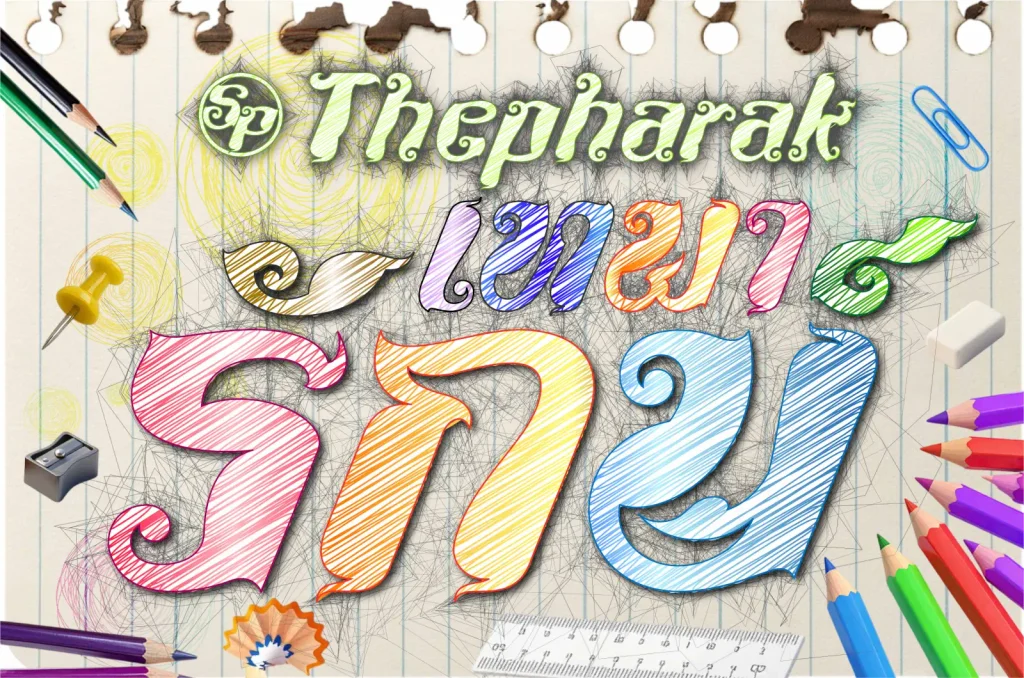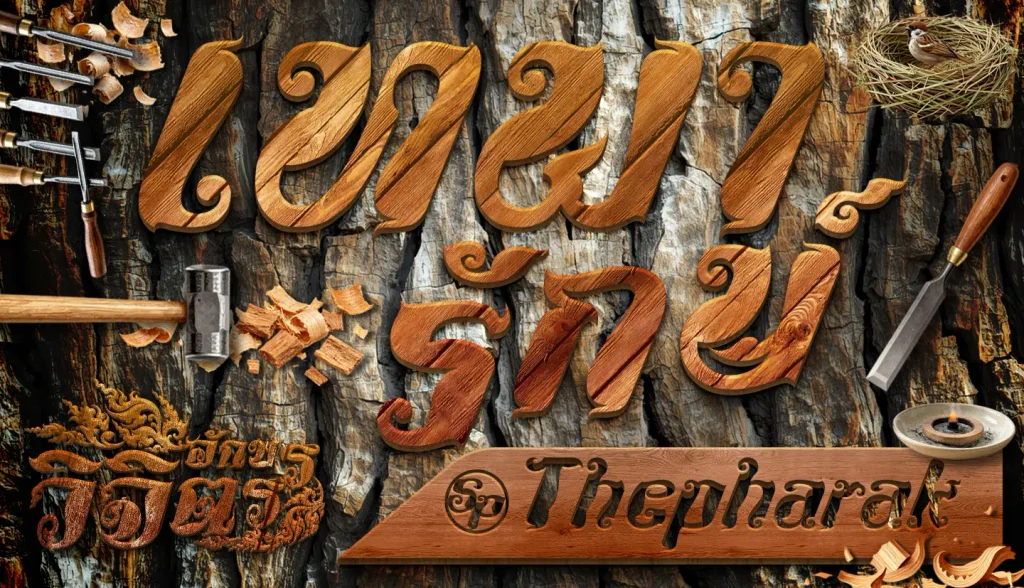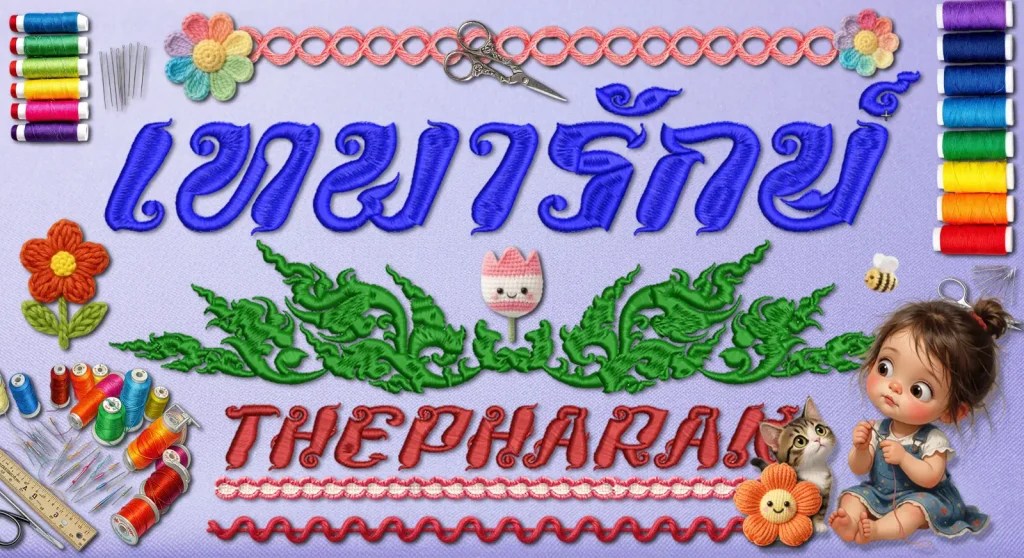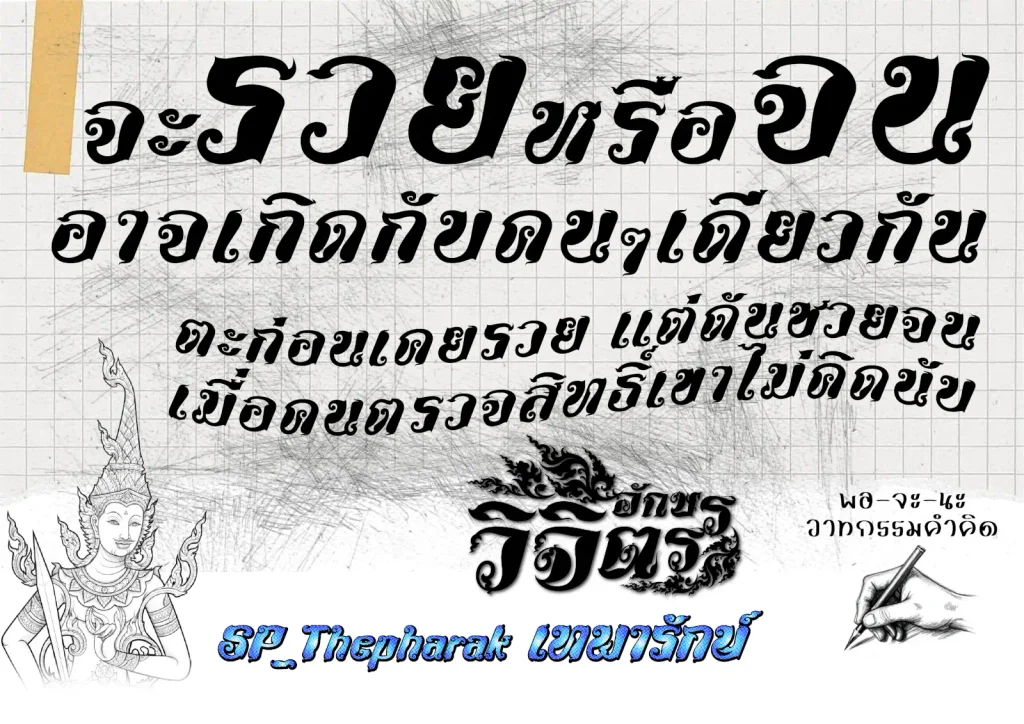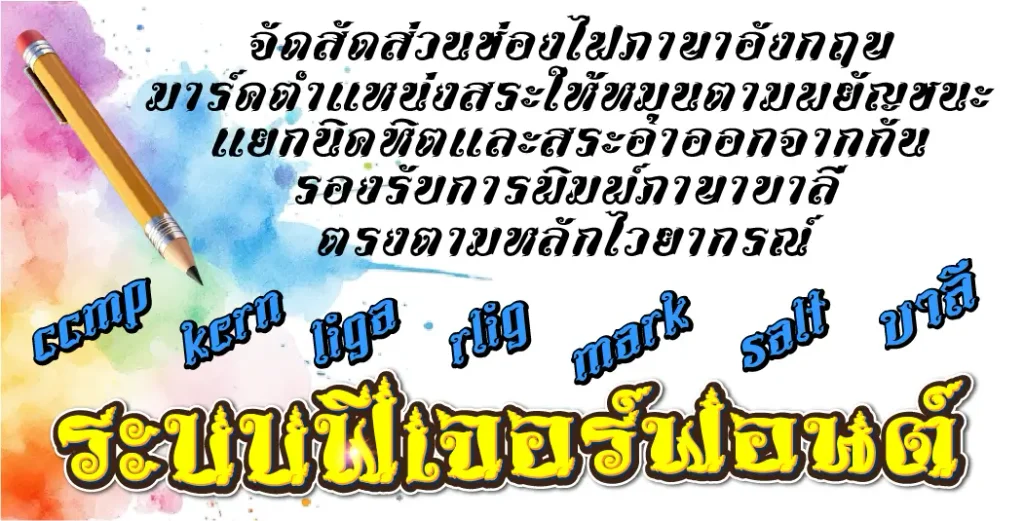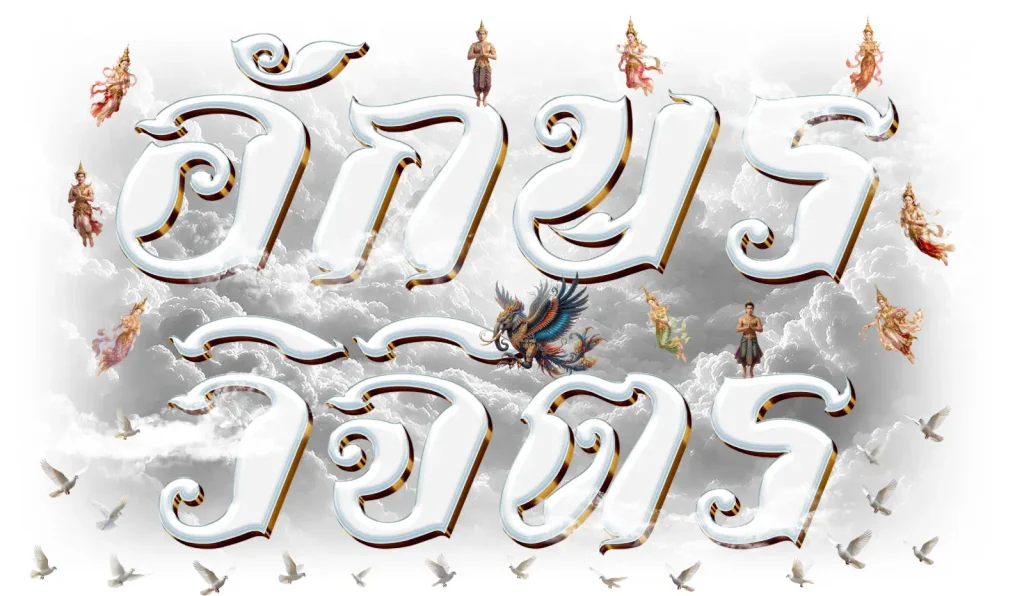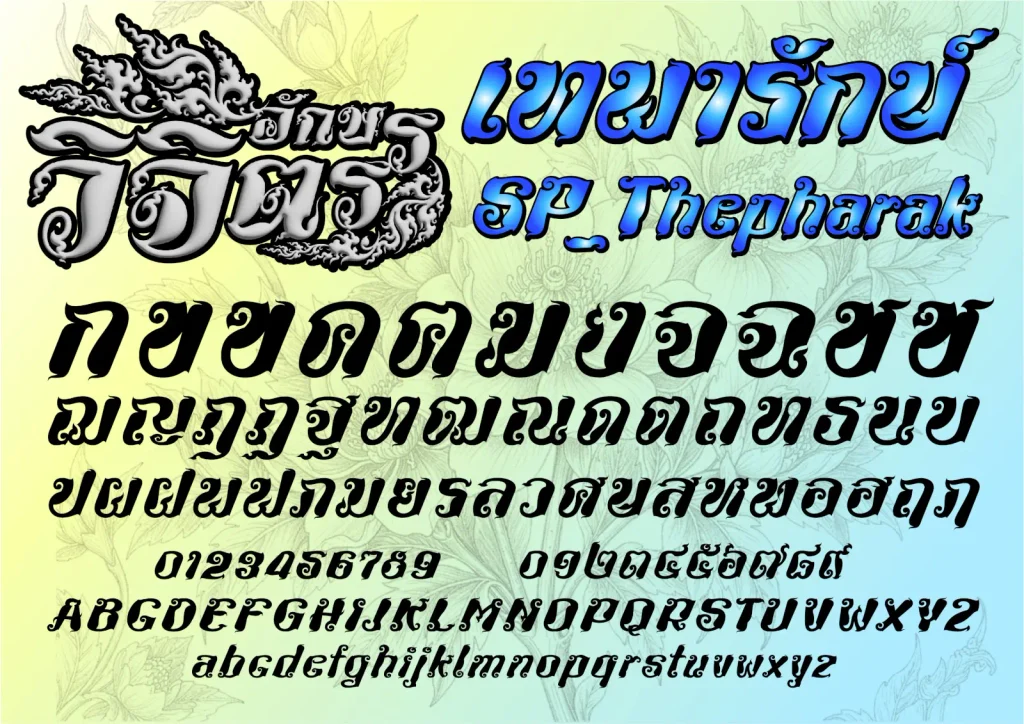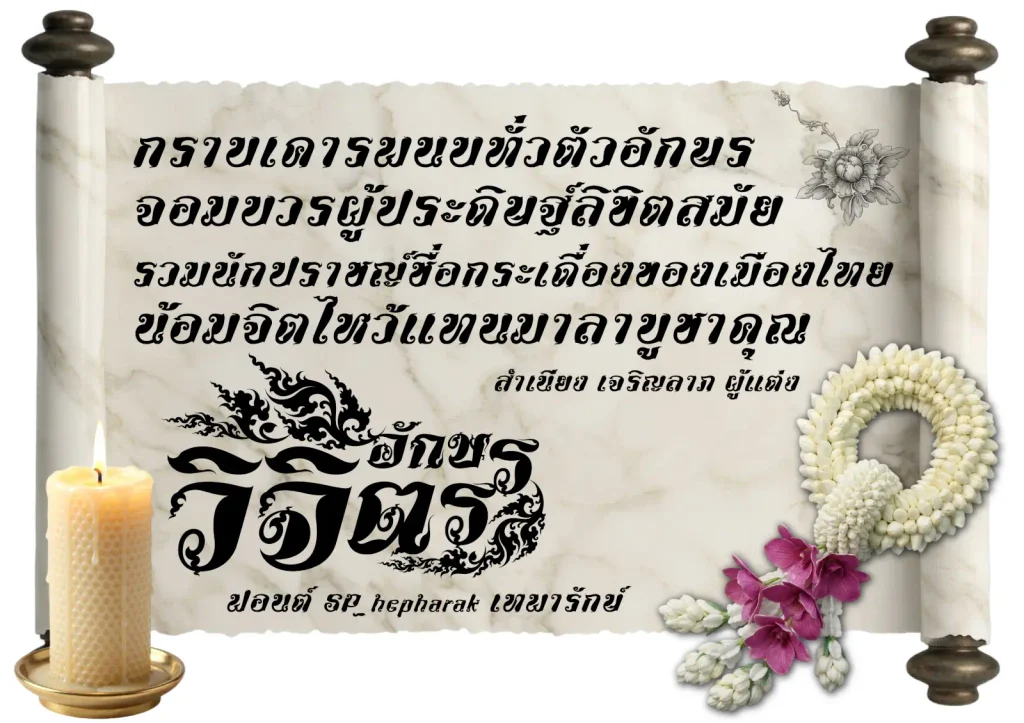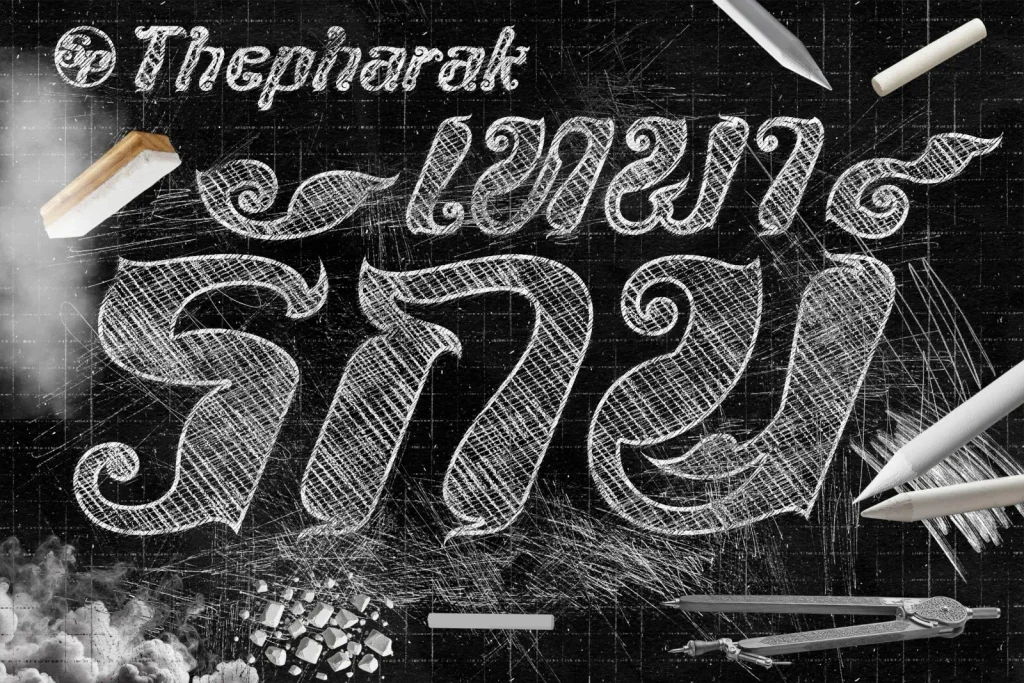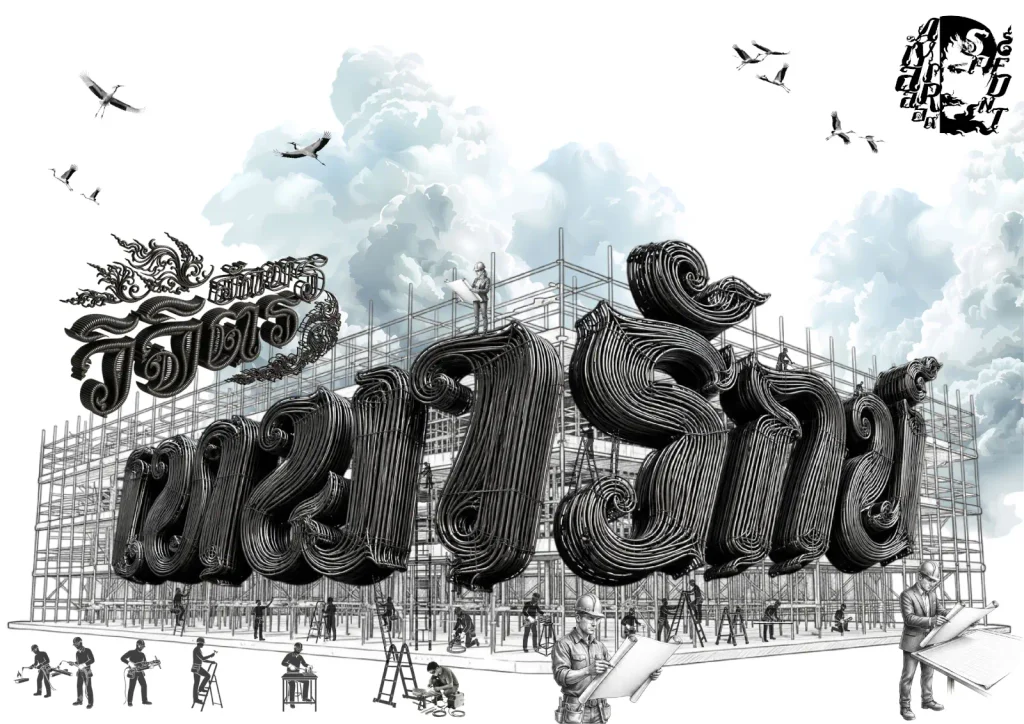
เทพารักษ์ (SP_Thepharak)
เทพารักษ์ (SP_Thepharak) – เป็นฟอนต์ที่อยู่ในโครงการอักษราสูตรไทยวิจิตร มุ่งเน้นการออกแบบลายเส้นให้กลมกลืนกับศิลปะลวดลายไทย
จัดรูปแบบอักษรให้เป็นเอกลักษณะเฉพาะตัว เข้ากันกับชุดอักษรนั้นๆ รวมถึงอักษรภาษาอังกฤษและสัญลักษณ์อื่นๆ ครบถ้วนบริบูรณ์
พร้อมใส่ฟีเจอร์ (แก้สระลอย-ล็อกเป้าเข้าพิกัด) เพื่อความสวยงามและลงตัว ไม่ว่าจะเป็นช่องไฟ สระวรรณยุกต์ ชั้นล่างชั้นบน และแยกนิคหิตเพื่อการใช้พิมพ์ภาษาบาลีไห้ถูกต้องตามหลักไวยากรณ์ ภายในฟอนต์ฟอนต์เดียว (Microsoft / Adobe ต้องเปิดค่ารองรับ)
ฟอนต์อักษรวิจตรชุดนี้ เหมาะสำหรับงานออกแบบเฉพาะด้าน เช่น โลโก้ ป้ายชื่อ สิ่งพิมพ์ โฆษณา งานเทศกาลพิเศษอื่นๆ เป็นอาทิ
ทั้งนี้ยังมีพรีเซนต์ข้อความสไตล์เอฟเฟกต์ ในรูปแบบต่างๆ เล็กน้อย เพื่อเป็นแนวทางในการใช้งานฟอนต์ของผู้สนใจทั่วไปด้วย
SP_FONT อักษรวิจิตร มุ่งเน้นสู่คุณค่าเอกลักษณ์ความเป็นไทย ใส่ใจทุกเส้นสายรายละเอียดศิลป์